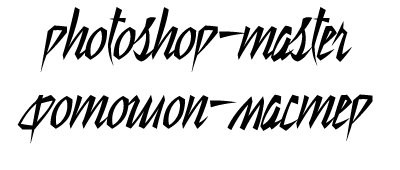
Шрифт - Still Time Cyr
Интересный шрифт, который хорошо подходит для работы в фотошопе. Есть поддержка русского языка.
если такой шрифт сделать кровавым будет очень здорово смотреться)))
сойдёт))приколльно
как то не очень *-*
Красиво.
Фактически это он и есть! Это просто написано китайской кистью, вот и всё! хЗЗЗ
на китайский похож))
Очень прикольный)))